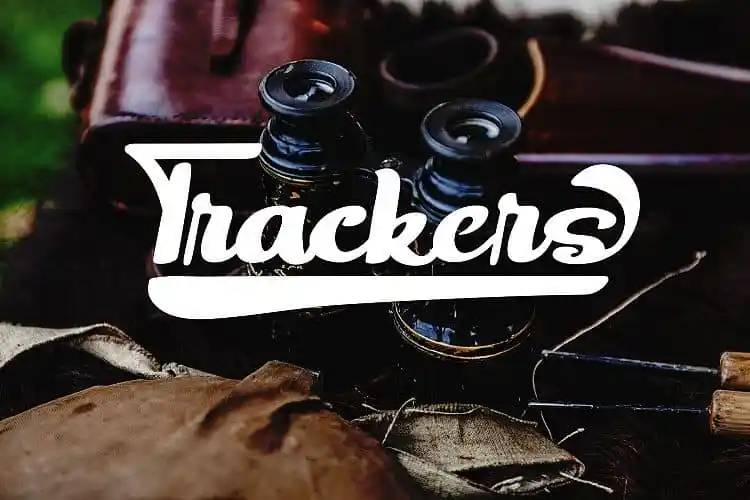
Trackers Bold Script Font – Download Grátis
Através do designer Naharstd chegou a nós uma nova fonte tipo Script chamada “Trackers Bold Script Font”. Esta fonte traz uma aparente audácia e elegância, com recursos de tipografia aberta que incluem muitas alternativas e swashes. Esses detalhes ajudam você a criar letrinhas memoráveis e inovadoras. A “Trackers Bold Script Font” é perfeita para uso em logotipos, subtítulos, capas de livros, panfletos, selos de marca, citações, embalagens de produtos, cabeçalhos, materiais de merchandising e até mesmo cartões de felicitações. Esta fonte é altamente versátil e pode ser usada em múltiplos idiomas, tornando-a uma excelente escolha para designers que desejam adicionar um toque único aos seus projetos visuais.